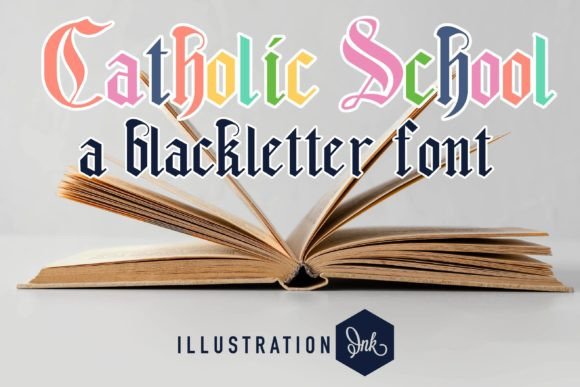
Catholic School
Ulasan Lengkap tentang Catholic School – Font Blackletter Klasik yang Memikat
Jika Anda sedang mencari font yang memancarkan keanggunan tradisional sekaligus menambahkan nuansa formalitas pada setiap proyek desain, Catholic School adalah pilihan yang tak boleh dilewatkan. Font ini mengusung gaya blackletter kuno dengan detail yang sangat khas, sehingga cocok untuk branding, undangan resmi, atau karya seni yang membutuhkan sentuhan timeless.
Kenapa Catholic School Menjadi Pilihan Utama Desainer?
- Gaya yang Sangat Distinct: Setiap huruf dirancang dengan detail kaligrafi yang rumit, menciptakan tampilan yang kuat dan mudah dikenali.
- Kesan Formal dan Elegan: Cocok untuk materi yang membutuhkan aura keagamaan, akademik, atau historis, seperti logo gereja, sertifikat, atau poster acara klasik.
- Readability yang Terjaga: Meskipun berkarakter blackletter, huruf-huruf utama tetap mudah dibaca, menjadikannya ideal untuk judul besar dan teks pendek.
Tips Mengoptimalkan Catholic School dalam Desain Anda
Untuk memaksimalkan potensi font ini, pertimbangkan beberapa strategi berikut:
- Padukan dengan Sans‑Serif Ringan: Kombinasikan judul menggunakan Catholic School dengan teks tubuh berjenis sans‑serif (mis. Open Sans) untuk keseimbangan visual.
- Gunakan Warna Netral atau Emas: Warna hitam, putih, atau emas akan menonjolkan keanggunan font tanpa mengurangi keterbacaan.
- Berikan Ruang Antar Huruf (Kerning) yang Tepat: Karena sifat blackletter yang rapat, sesuaikan spacing agar tidak terasa sesak.
- Manfaatkan dalam Header dan Logo: Font ini sangat efektif untuk header website, logo institusi, atau judul buku yang ingin memberi kesan tradisional.
Kesimpulan – Catholic School, Font Blackletter yang Menyatu dengan Klasik
Dengan gaya yang tak lekang oleh waktu dan kesan formal yang kuat, Catholic School menjadi pilihan utama bagi desainer yang ingin menambahkan sentuhan elegan pada karya mereka. Baik untuk proyek pribadi maupun branding komersial, font ini dapat membantu Anda menciptakan desain yang spectacular dan penuh karakter.